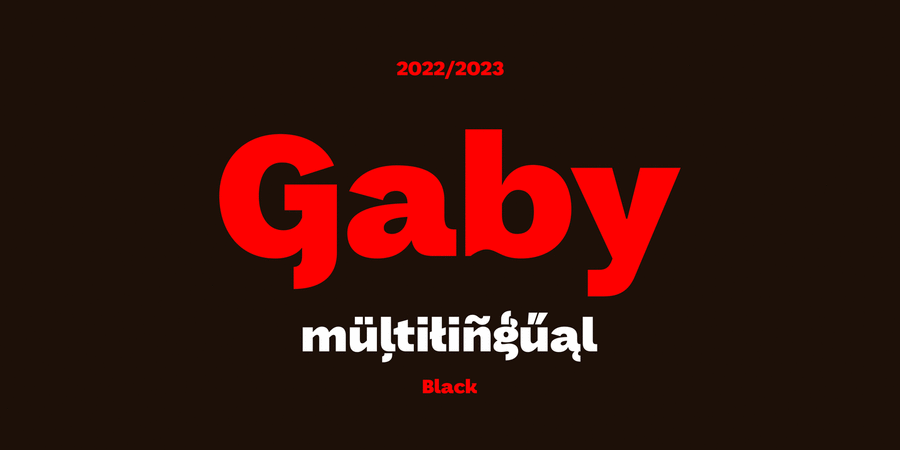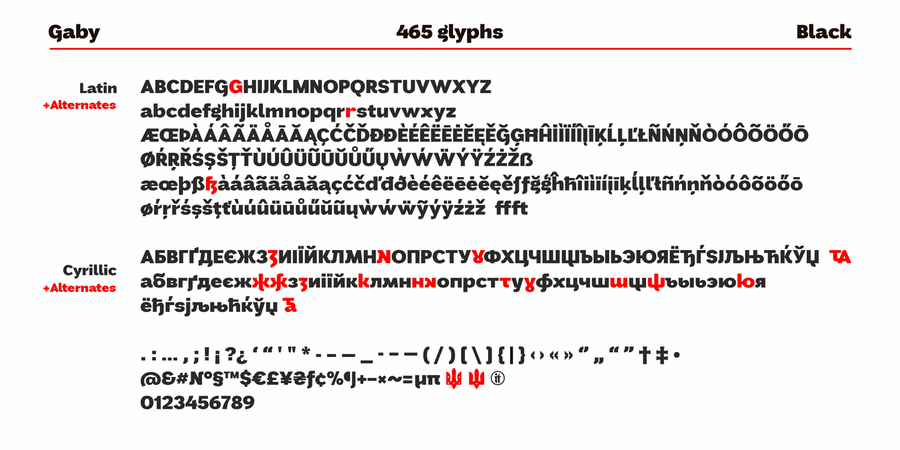
Gaby Black – потужний гротеск з широкими пропорціями та дружнім характером. Містить більшість знаків Latin Pro, кирилицю та альтернативні літери української кирилиці, а також експериментальний український двоскладовий амперсанд для заголовкових та малих літер (ТА, та). Застосування: акциденція, візуальна ідентифікація, видавництво, соціальні та індивідуальні проєкти тощо. Шрифт розробила Тетяна Іваненко у 2022-2023 році.